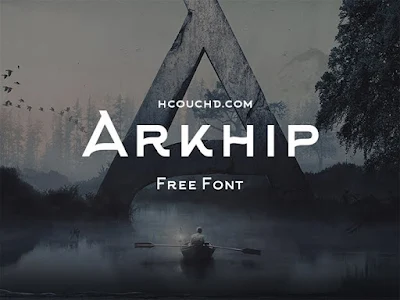
خط Arkhip Typeface هو خط روسي الأصل و متوفر أيضا بنسخة لاتينية، رائع و بسيط مجاني، و هو من تصميم Klimov Design، يمكنك تحميل هذا خط مجانا من رابط أسفله…